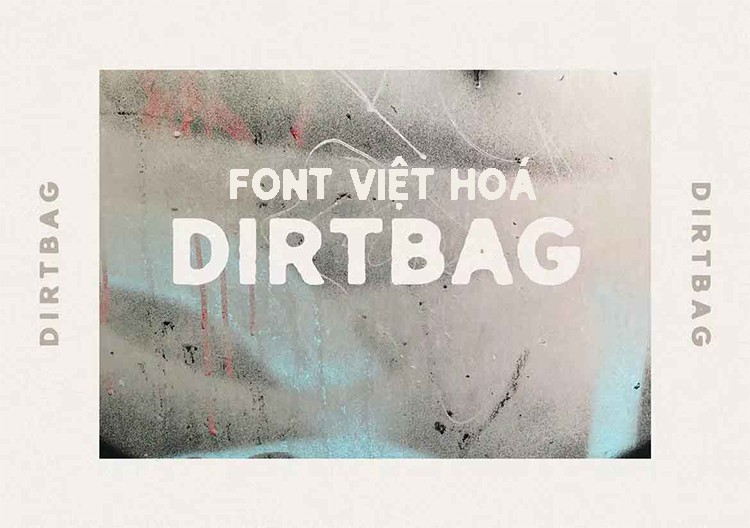
Tải Ngay Font việt hoá MJ Dirtbag ( Gõ chữ thường ) – Phong Cách Graffiti Độc Đáo
Giới thiệu về Font việt hoá MJ Dirtbag ( Gõ chữ thường )
Trong thế giới thiết kế đồ họa hiện đại, việc lựa chọn một bộ Font Chữ phù hợp đóng vai trò quan trọng trong việc truyền tải thông điệp. Font việt hoá MJ Dirtbag ( Gõ chữ thường ) là một sự lựa chọn tuyệt vời dành cho những ai yêu thích phong cách đường phố đầy cá tính. Với các đường nét mạnh mẽ và phóng khoáng, bộ phông này mang lại hơi thở của nghệ thuật Graffiti vào từng tác phẩm. Đặc biệt, phiên bản gõ chữ thường giúp các nhà thiết kế dễ dàng tạo ra những bố cục tự nhiên và mượt mà hơn.
Tại sao nên sử dụng Font việt hoá MJ Dirtbag ( Gõ chữ thường )?
Bộ font này được tối ưu hóa hoàn toàn cho tiếng Việt, giúp bạn không còn lo lắng về lỗi hiển thị dấu. MJ Dirtbag cực kỳ phù hợp cho các dự án thiết kế poster âm nhạc, bìa sách hoặc trang trí áo thun cho học sinh. Khác với các kiểu chữ truyền thống, Font việt hoá MJ Dirtbag ( Gõ chữ thường ) tạo nên sự phá cách nhưng vẫn giữ được độ dễ đọc cần thiết. Đây là công cụ hữu ích để các bạn trẻ thỏa sức sáng tạo trong không gian học đường và nghệ thuật số.
Cách ứng dụng Font việt hoá MJ Dirtbag ( Gõ chữ thường ) hiệu quả
Để tận dụng tối đa vẻ đẹp của bộ chữ, bạn nên kết hợp với các gam màu tương phản cao. Việc sử dụng Font việt hoá MJ Dirtbag ( Gõ chữ thường ) trong các tiêu đề lớn sẽ tạo ra điểm nhấn thị giác mạnh mẽ. Bên cạnh đó, bạn có thể thêm các hiệu ứng đổ bóng hoặc viền ngoài để tăng thêm chiều sâu cho thiết kế của mình.